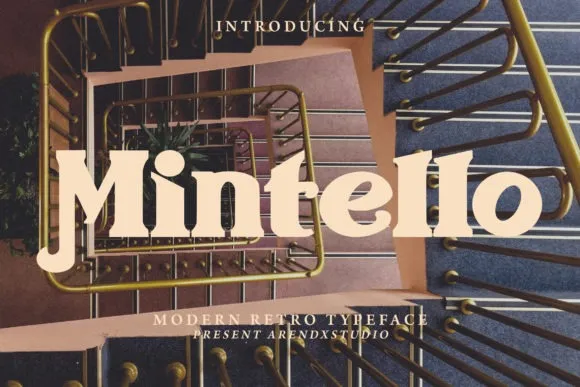
Descubra Mintello Font, uma elegante tipografia serif que irá enriquecer seus projetos criativos no design do Brasil. Criada por Arendxstudio, Mintello é um tipo vintage com alternativas estilizadas, perfeitamente adaptável a diversos tipos de design. Esta fonte multifuncional vai elevá-los ao nível mais alto, oferecendo uma versatilidade incrível que permite usá-la em múltiplos ambientes gráficos. Mintello é uma ótima adição para quem busca um estilo sofisticado e elegante, ou aqueles que buscam uma tipografia vintage moderna. Adicione a sua próxima ideia criativa à lista de projetos e observe como ela ganha vida ao utilizar Mintello. Aqui no Brasil, onde as cores vibrantes contrastam com o entrelaçamento sereno dos nossos recursos naturais, esta fonte traz um toque de sofisticação à paleta de criações gráficas brasileiras.